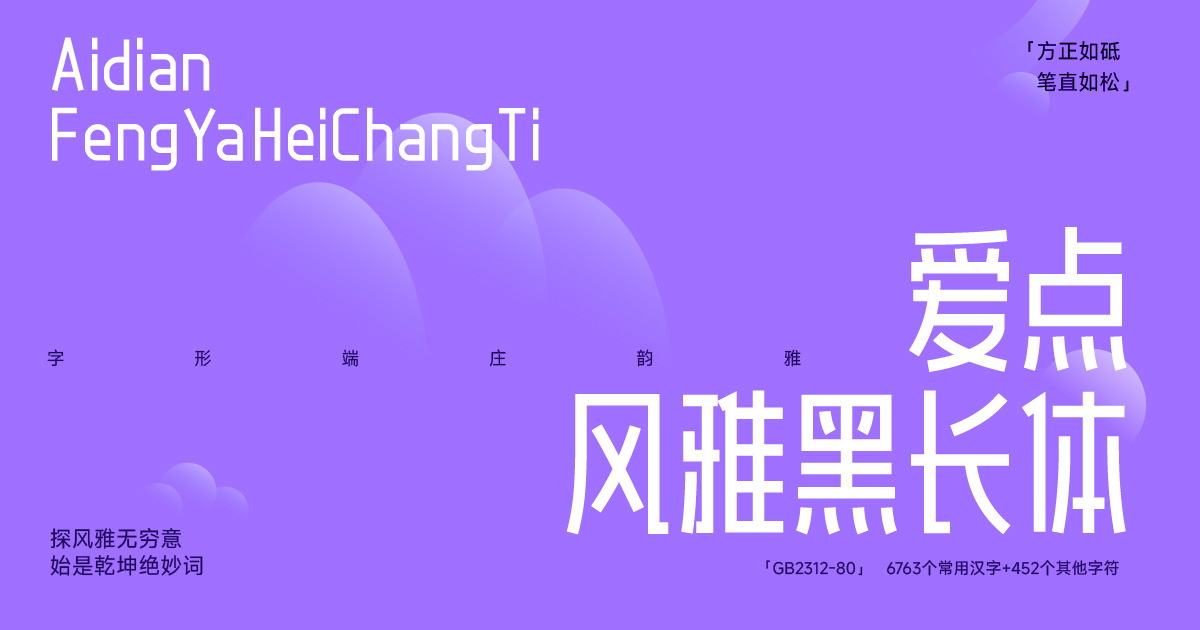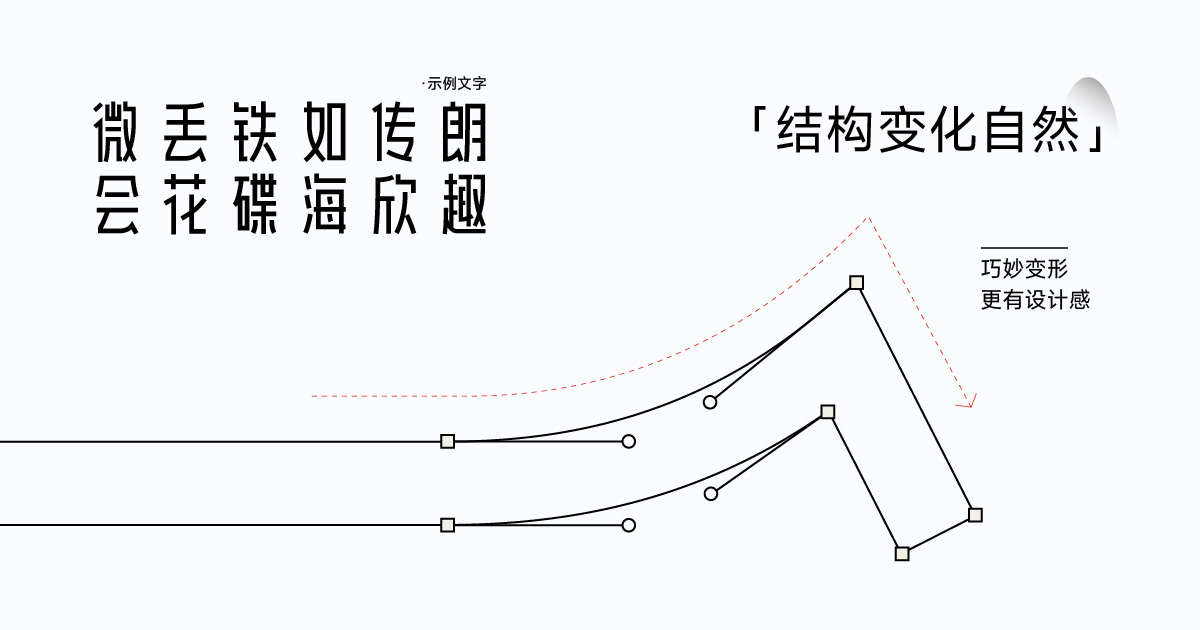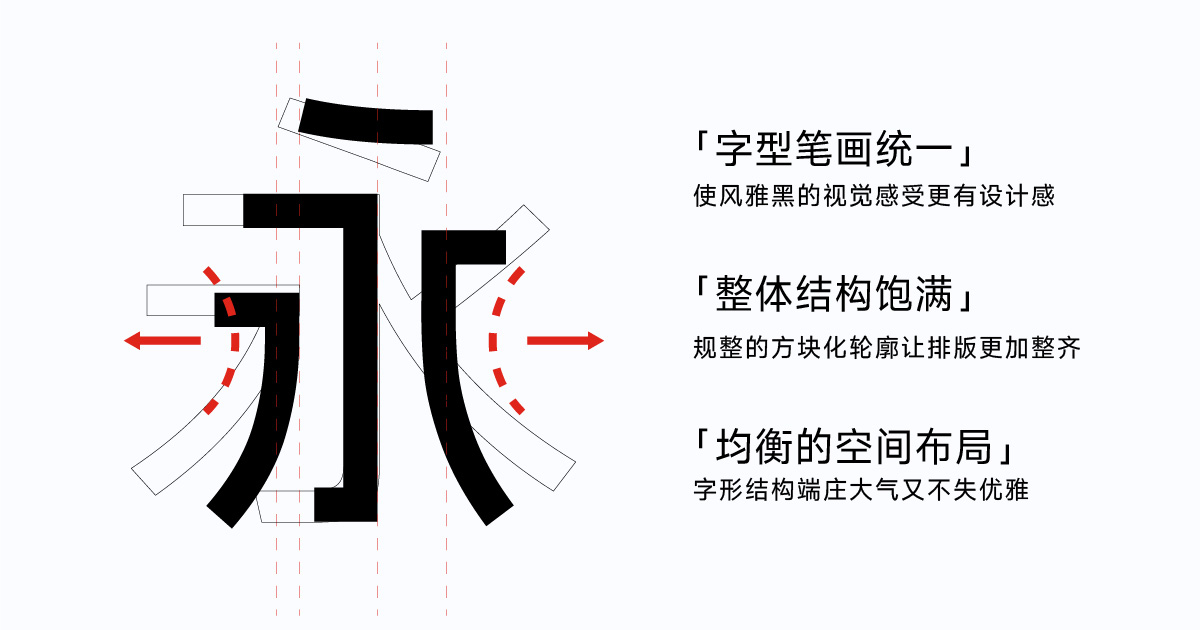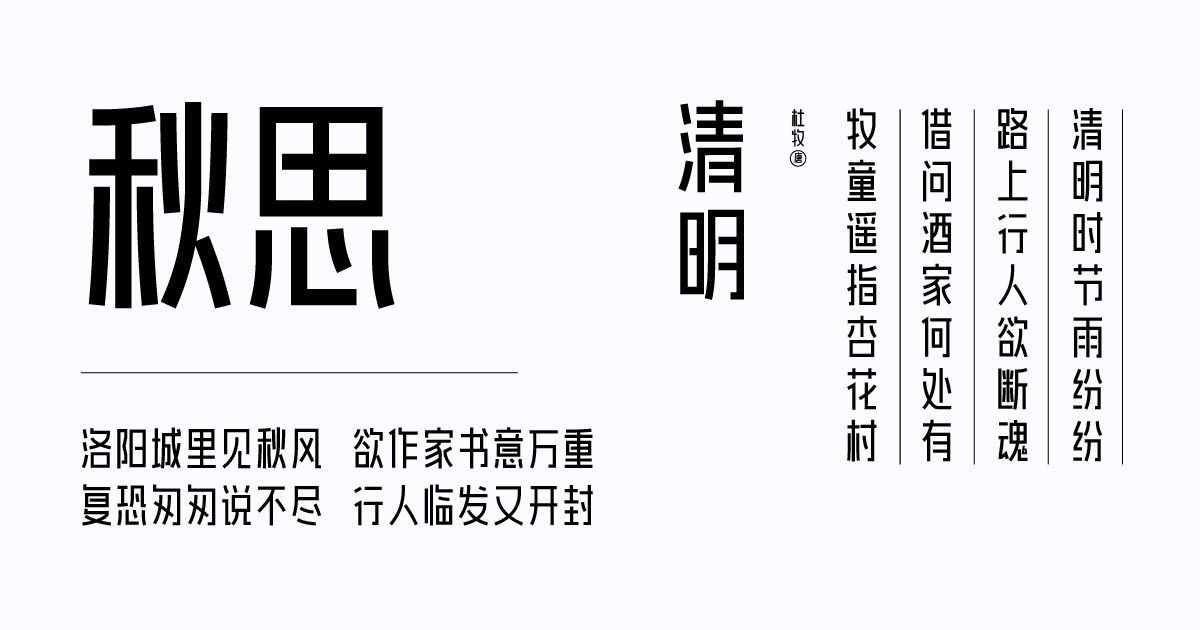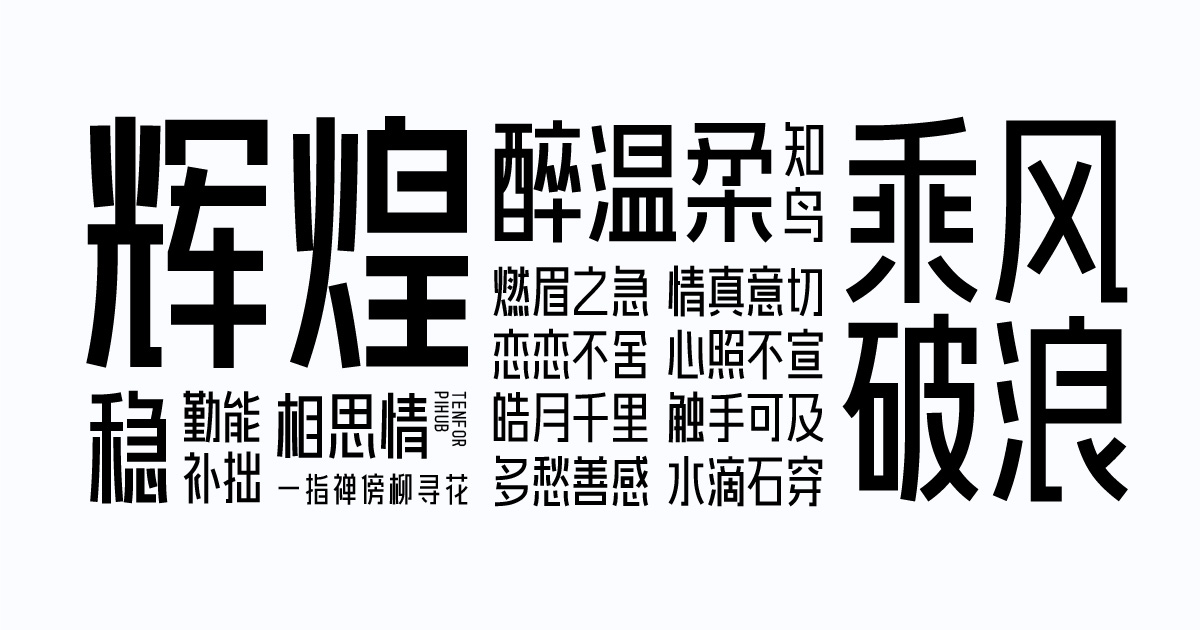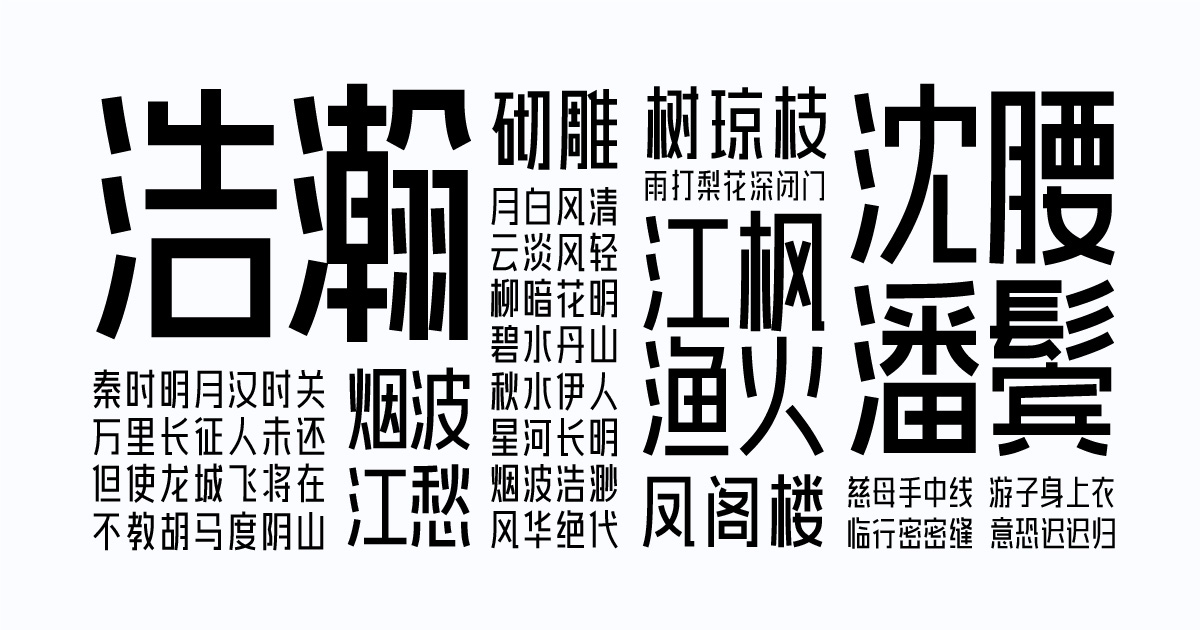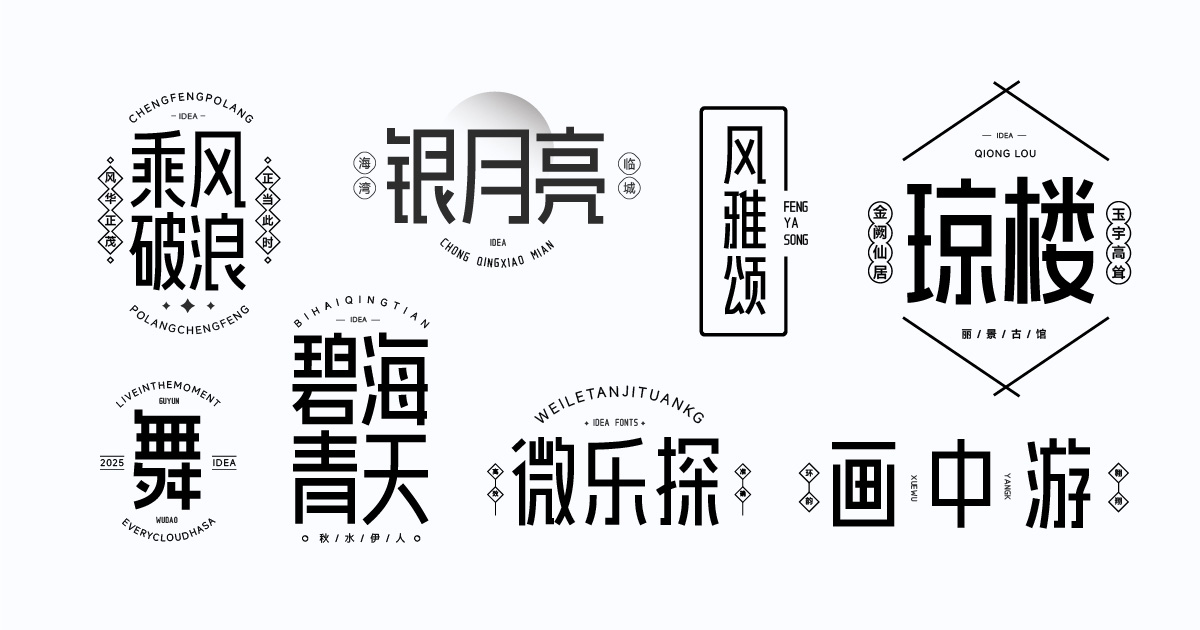
爱点风雅黑长体
爱点风雅黑长体是广州爱点视觉文化有限公司基于 “爱点风雅黑” 开发的商用免费字体,个人及企业可永久免费用于广告、UI 设计、平面设计、视频字幕等场景,但不可修改字体、制作衍生版本,也不可用于商标注册、出版物等用途。其字符集符合 GB2312-80 标准,包含 6763 个常用汉字及 452 个其他字符,能满足日常多数文字需求。
该字体形态高挑时尚,风格端庄韵雅,笔画方正如砥且纤细有力,首尾过渡流畅,兼具正直稳重感与独特艺术美,适用于时尚广告、高端包装、艺术海报等场景,可为作品增添优雅精致的气质。